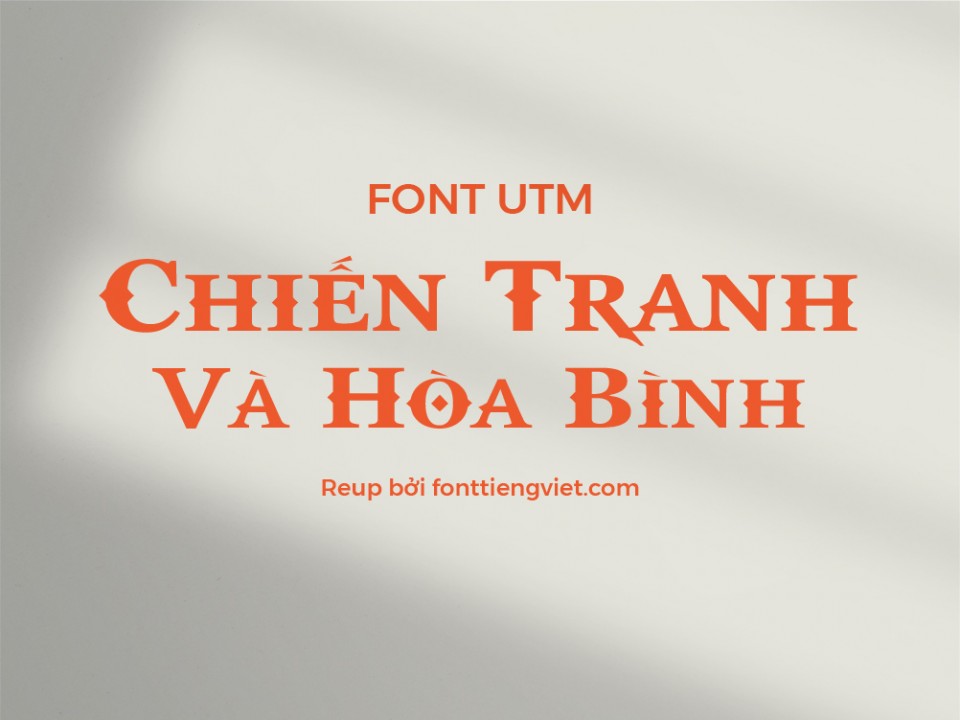
Font việt hóa UTM Than Chien Tranh
Tải Font việt hóa UTM Than Chien Tranh Miễn Phí Cho Thiết Kế Ấn Tượng
Giới thiệu về Font việt hóa UTM Than Chien Tranh
Trong thế giới đồ họa, việc lựa chọn một Font Miễn Phí phù hợp đóng vai trò quyết định đến linh hồn của tác phẩm. Font việt hóa UTM Than Chien Tranh là một trong những bộ phông chữ đặc biệt nhất thuộc hệ thống UTM, được cộng đồng thiết kế tại Việt Nam ưa chuộng nhờ phong cách mạnh mẽ và đầy cá tính. Với các đường nét góc cạnh, mô phỏng phong cách chữ cổ điển nhưng không kém phần hiện đại, bộ font này cực kỳ phù hợp cho các dự án yêu cầu sự kịch tính, uy nghiêm hoặc mang hơi hướng sử thi. Việc cài đặt và sử dụng vô cùng đơn giản trên nhiều phần mềm thiết kế phổ biến hiện nay.
Ưu điểm nổi bật của Font việt hóa UTM Than Chien Tranh
Phong cách thiết kế độc bản
Đúng như tên gọi, Font việt hóa UTM Than Chien Tranh mang đến cảm giác về sức mạnh và sự kiên cường. Các ký tự được thiết kế với độ dày lớn, tạo điểm nhấn thị giác cực mạnh ngay từ cái nhìn đầu tiên. Điều này giúp các nhà thiết kế dễ dàng tạo ra những tiêu đề nổi bật cho bìa sách, poster phim hành động hoặc các biểu ngữ quảng cáo sự kiện thể thao.
Khả năng hiển thị tiếng Việt hoàn hảo
Điểm cộng lớn nhất chính là bộ font đã được việt hóa hoàn chỉnh, giúp người dùng không còn lo lắng về lỗi font hay thiếu dấu khi gõ tiếng Việt. Sự tỉ mỉ trong quá trình xử lý dấu thanh giúp văn bản giữ được tính thẩm mỹ đồng nhất và chuyên nghiệp nhất.
Ứng dụng và cách tải Font việt hóa UTM Than Chien Tranh